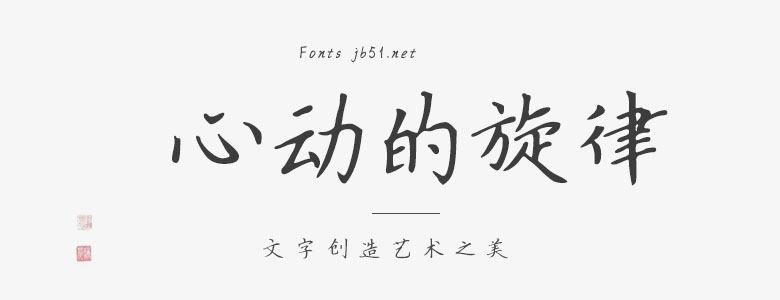
當(dāng)我看到你,我的心就會(huì)跳動(dòng)不已,你是我生命中最美的旋律。該字體是在國(guó)家標(biāo)準(zhǔn)簡(jiǎn)體字庫(kù)GB2312所包含6763漢字的基礎(chǔ)上,又增加了近200常用字,已經(jīng)覆蓋了大陸99.75%的漢字使用頻率,足以滿足日常需求,適合于文化類的宣傳設(shè)計(jì)、商業(yè)類品牌的廣告和產(chǎn)品包裝設(shè)計(jì)以及個(gè)性化文字排版等較多場(chǎng)景。